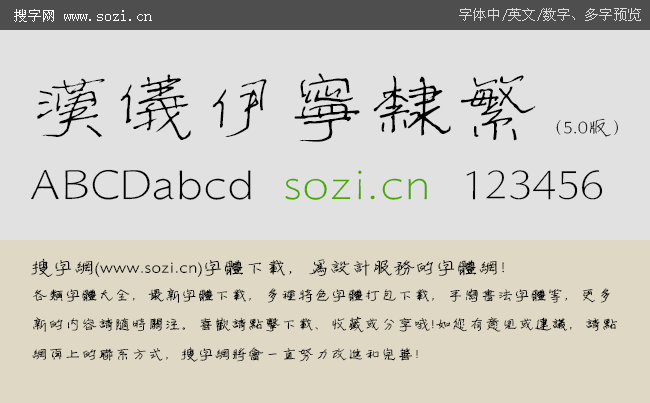
漢儀伊寧隸繁
搜字網(wǎng)提供一款漢儀伊寧隸繁中文字體下載,漢儀伊寧隸是行書與隸書的融合體,具有行書的流暢、瀟灑、隨意與隸書的雅致,書寫講究特征,這在書法(毛筆書寫)中很常見,其特征為:流暢、雅致、樸拙、隨意而有不失講究。用硬筆書寫實(shí)不多見,是一次極具積極意義,拓展性質(zhì)的實(shí)踐。適用于廣告設(shè)計(jì)、平面設(shè)計(jì)、印刷包裝、藝術(shù)設(shè)計(jì)、網(wǎng)站設(shè)計(jì)領(lǐng)域。